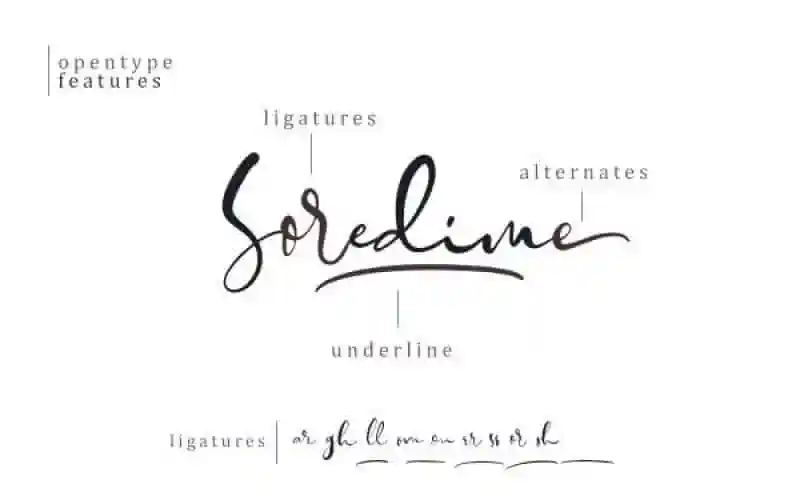
Soredime – Signature Font – Download Grátis
A Soredime é uma fonte Signature que apresenta uma experiência visual única para designers de todo o Brasil. Com suas letras manuscritas cuidadosamente elaboradas, a Soredime oferece um estilo elegante e autêntico ideal para ambientes como moda, marcas, catálogos e designs criativos. Suas características incluem alternativas de letras, ligaturas e sublinhado, o que oferece grande flexibilidade na criação de logotipos para marcas ou em outros projetos de branding. A fonte suporta várias línguas, tornando-a perfeita para design internacional. Para designers brasileiros que valorizam a estética delicada e sofisticada dos escritos autênticos, a Soredime é uma escolha ótima para criar identidades visuais memoráveis. Além disso, sua PUA Encodada permite maior versatilidade na manipulação da fonte em qualquer software de edição de arte ou design gráfico. O resultado? Uma fonte que não apenas atende a sua necessidade de criação de design, mas oferece também uma paleta de recursos práticos para simplificar e acelerar o processo.